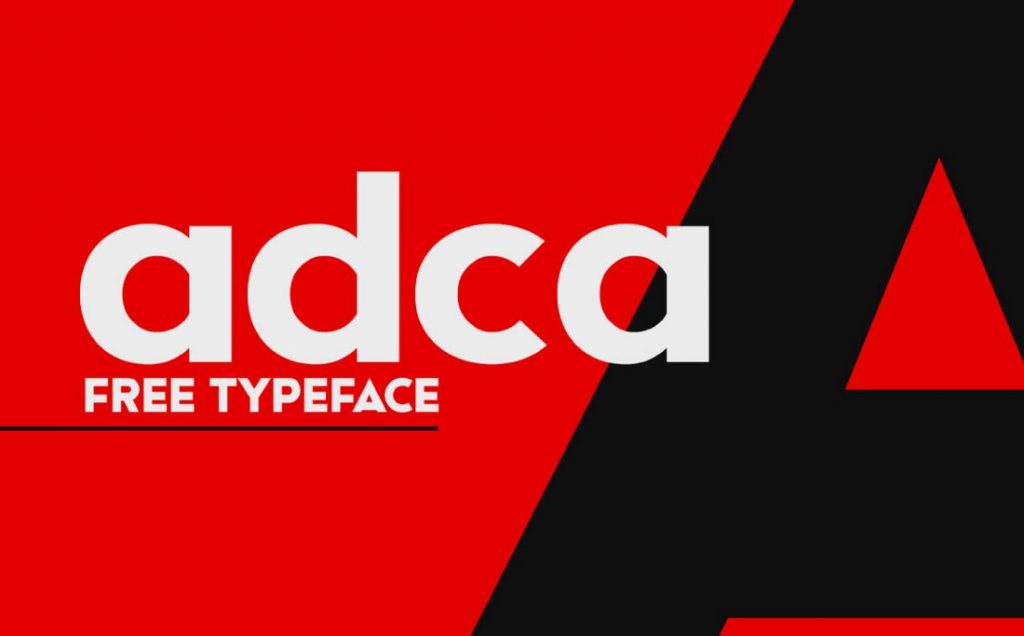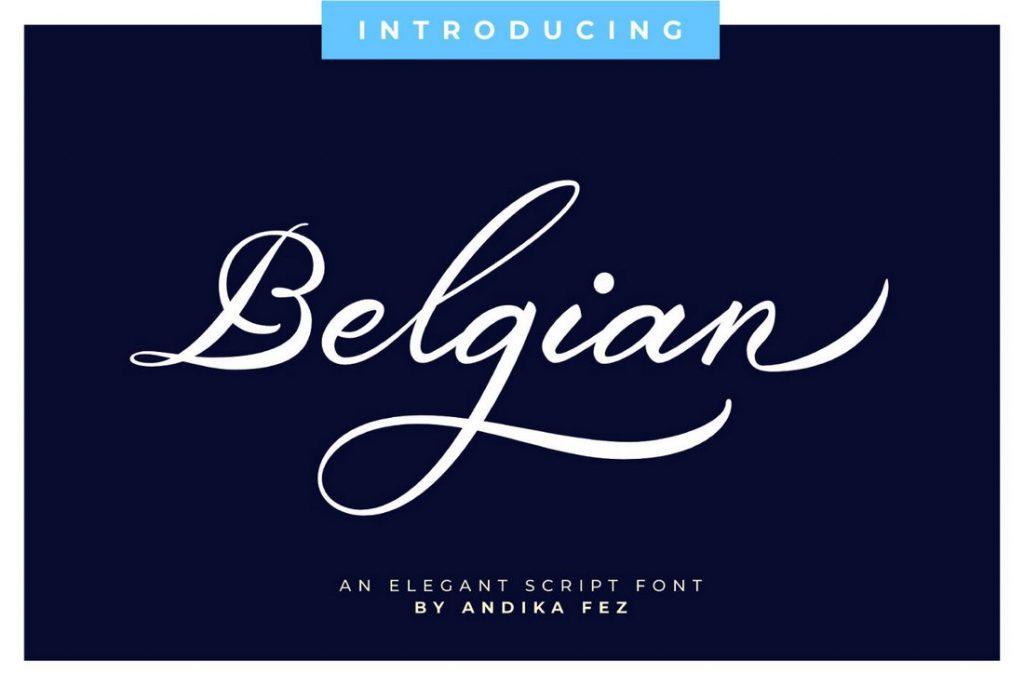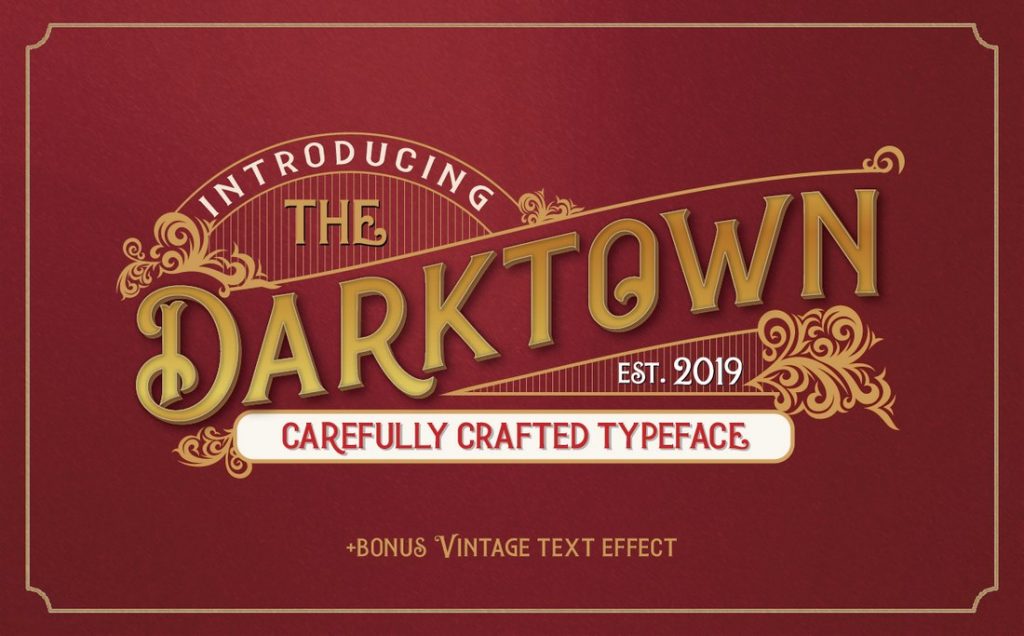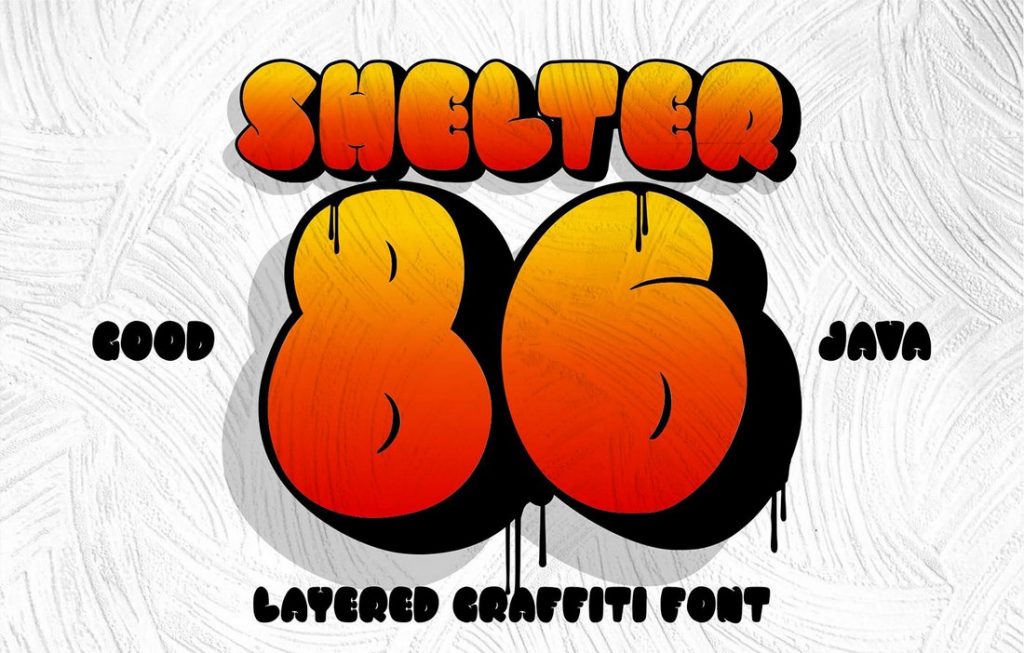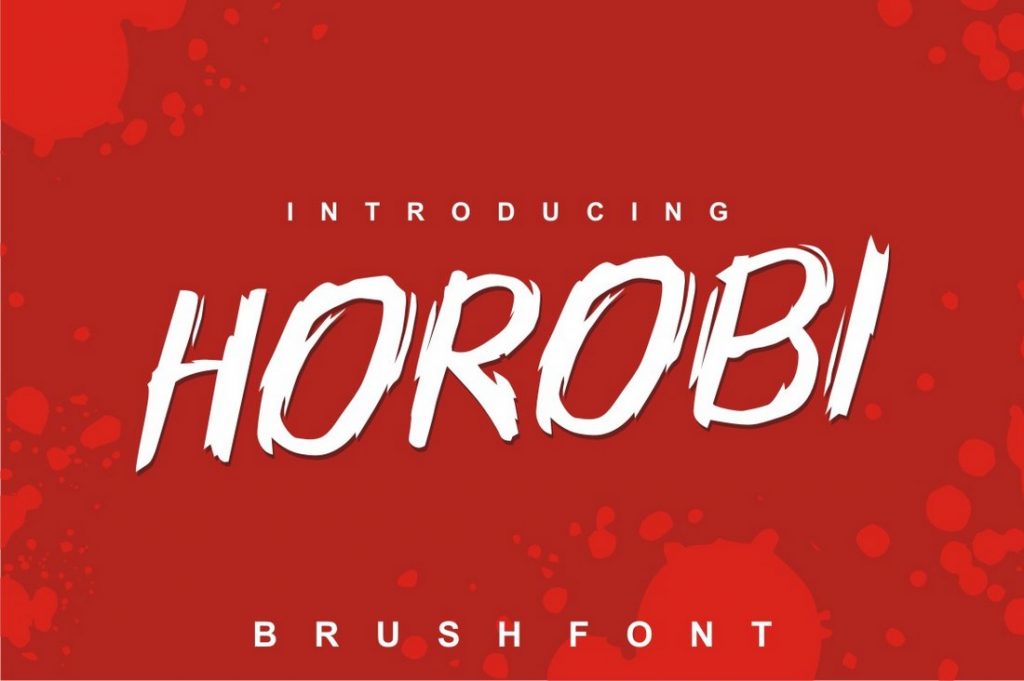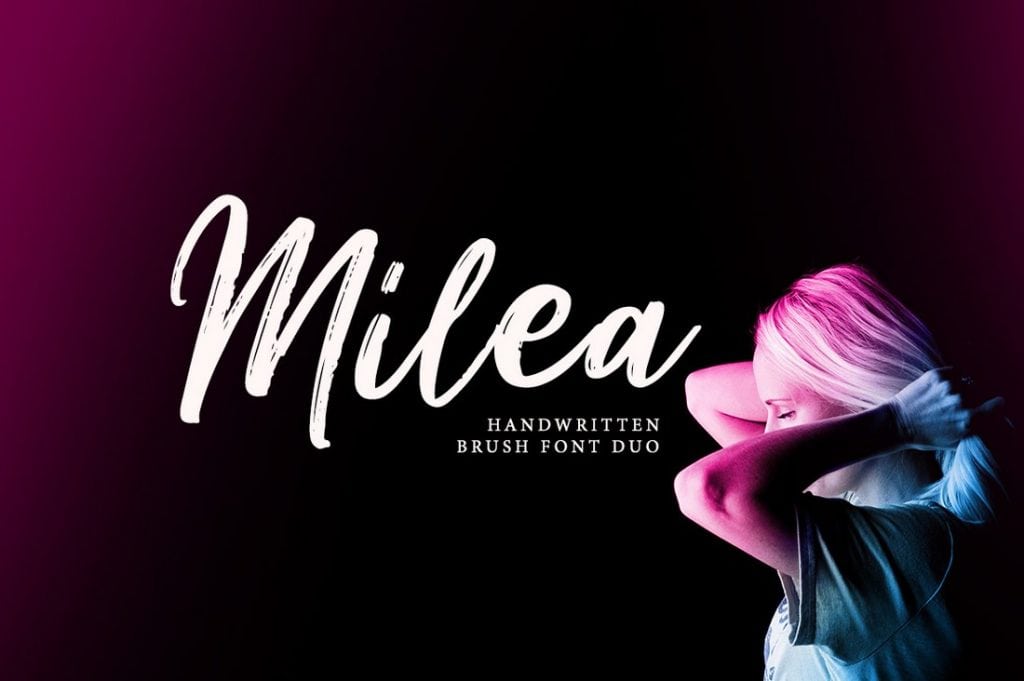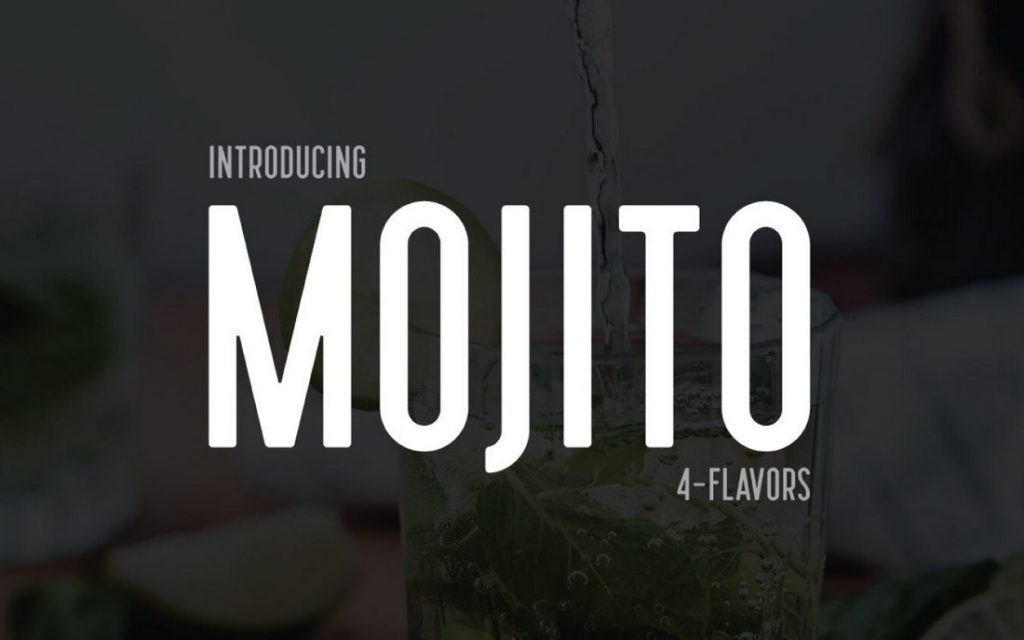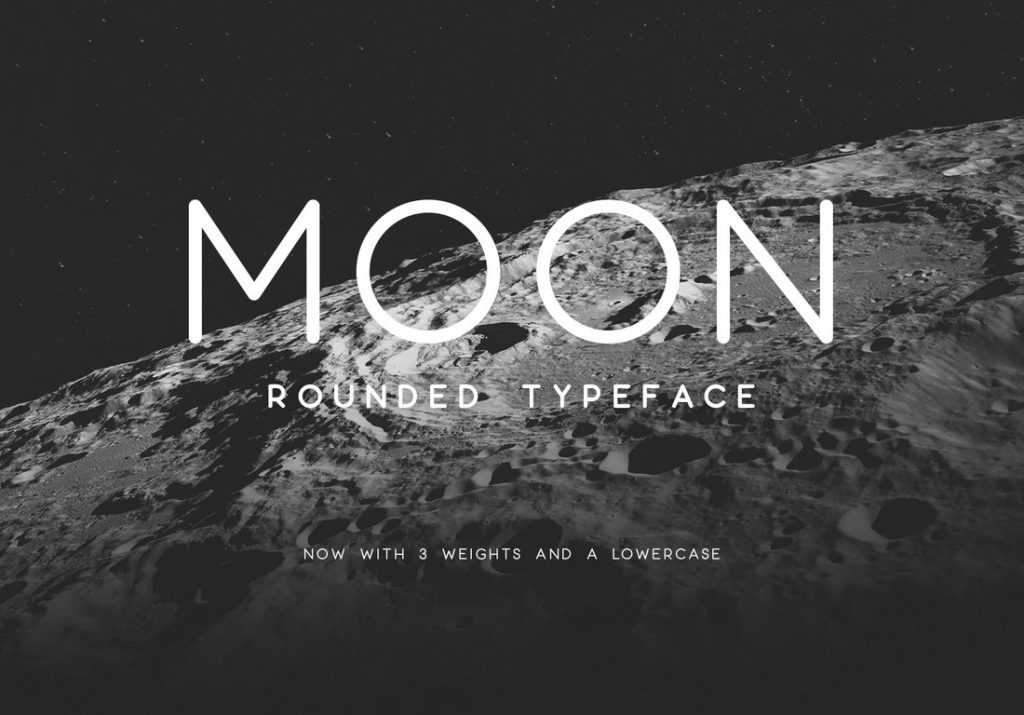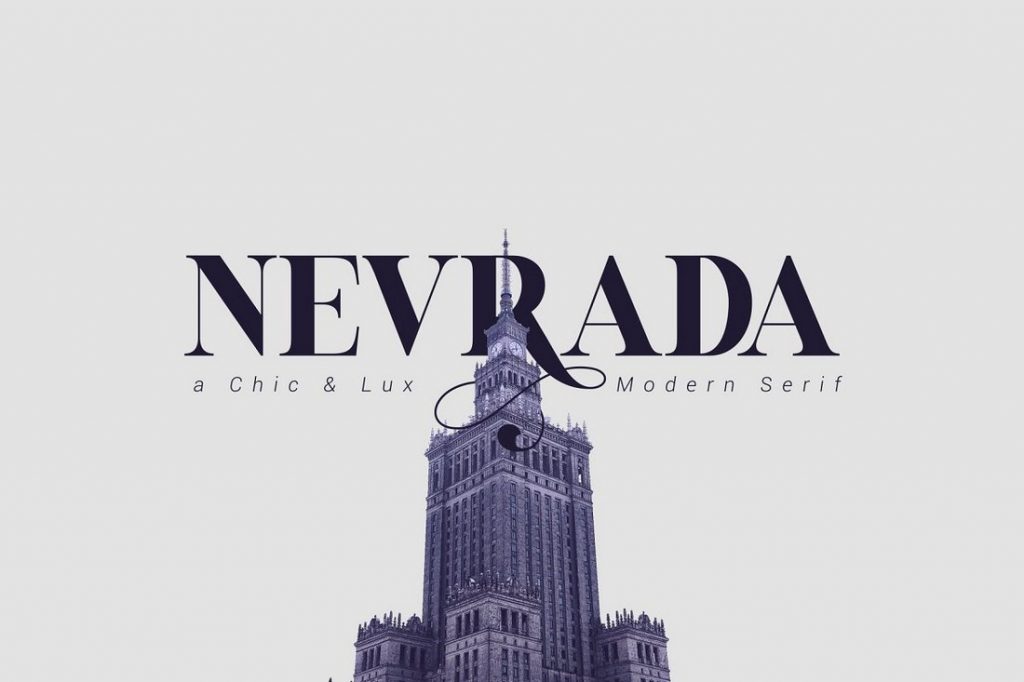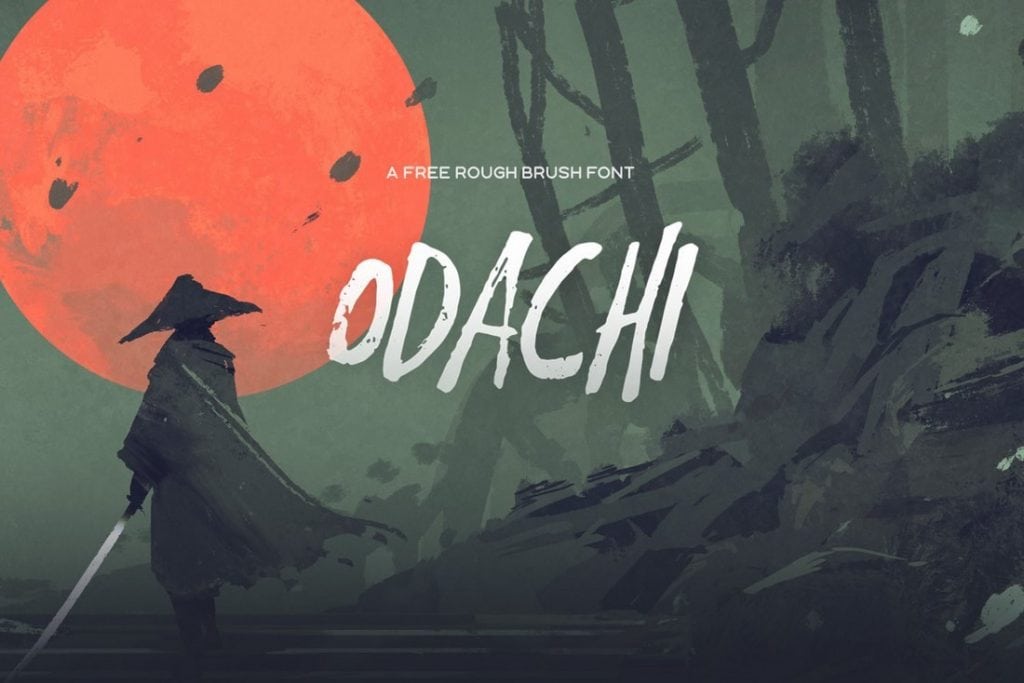
今天我們收集和整理了一些免費的字體,你將對這些字體的數(shù)量和質(zhì)量感到驚訝。 尤其是對網(wǎng)站設(shè)計或平面設(shè)計師來說,無論你是要正在尋找合適的襯線,腳本還是無襯線字體,今天希望你可以找到適合你的優(yōu)秀的免費字體!
使用美觀的字體是使任何類型的設(shè)計看起來更加專業(yè)的關(guān)鍵部分。 當然,你不必總是使用高級字體來達到相同的專業(yè)水平。 如果你無力花錢購買高級字體來使設(shè)計更加美觀,可以隨時使用數(shù)千種免費字體中的一種。
此集合中包括免費的腳本字體,襯線字體,無襯線字體,裝飾字體,以及更多與你正在從事的任何設(shè)計項目相匹配的字體。 繼續(xù),向下滾動并開始搜索下載吧。
1.Potra – Free Futuristic Font
Potra是一款具有未來派設(shè)計的現(xiàn)代字體。 該字體非常適合用于制作社交媒體帖子,T恤,網(wǎng)站設(shè)計中的標題等。
2.Milea Handwritten Brush Font
Milea是一款優(yōu)雅的筆刷字體,具有自然的手寫風格。 從書籍封面到結(jié)婚請柬,網(wǎng)站設(shè)計,博客等等,你都可以使用它來幫助你添加更多的視覺亮點。
3.Moon – Modern Rounded Typeface
Moon是一款帶有圓角字符設(shè)計的精美極簡風格無襯線字體。 該字體非常適合用于設(shè)計從網(wǎng)站設(shè)計到海報標題等等的所有內(nèi)容。
4.Nanotech – Free Clean Sans-Serif Font
Nanotech是現(xiàn)代無襯線字體,具有專業(yè)的設(shè)計。 從設(shè)計網(wǎng)站標題到海報標題,徽標等等,它都是理想的選擇。
5.ADCA – Free Bold Geometric Font
ADCA是一種使用幾何設(shè)計理念而制作的字體。 該字體可完全免費用于你的個人和商業(yè)項目。
6.Highfield – Free Luxury Sans-Serif Font
Highfield是設(shè)計奢侈品牌徽標,徽章和標牌的理想字體。 該字體可免費用于你的個人項目。
7.Belgian Signature – Free Elegant Script Font
這款優(yōu)雅的免費腳本字體具有精美時尚的設(shè)計,使其適合幾乎所有類型的不管是平面還是數(shù)字網(wǎng)頁設(shè)計,同時它可以免費用于個人和商業(yè)項目。
8.Mojito – Free Semi-Condensed Font
Mojito具有高且窄的字符設(shè)計,使其最適合設(shè)計海報和網(wǎng)頁設(shè)計中的標題。 你可以將其免費用于個人項目。
9.Tahu – Free Script Font
Tahu是一款具有簡約設(shè)計的現(xiàn)代腳本字體。 非常適合用于T恤設(shè)計,網(wǎng)站標題和社交媒體帖子。 該字體可免費用于個人和商業(yè)項目。
10.Odachi – Free Brush Font
Odachi是一款帶有粗糙設(shè)計的優(yōu)雅免費畫筆字體。 可以完全免費用于你的商業(yè)項目。 它也包括數(shù)字,替代和標點符號。
6種流行字體樣式
如果你是設(shè)計新手,那么對不同類型的字體及其使用方法有基本的了解就很重要。
1.襯線字體(Serif Fonts)
在某些字體中,你會在字符的邊緣看到較細的線條設(shè)計,擁有這個特征的字體一般稱為襯線字體。 襯線字體是具有精美字體設(shè)計的字體,它們主要用于專業(yè)和商業(yè)設(shè)計。
2.無襯線字體(Sans-Serif Fonts)
無襯線字體是具有清晰字符設(shè)計的字體。 這些字體中的字符的邊緣沒有任何線(或襯線)。 Sans-serif字體通常用于創(chuàng)意和休閑類型的設(shè)計中,而且眾所周知,它們還可以提高可讀性。
3.腳本&手寫字體(Script & Handwriting Fonts)
這些是具有漩渦狀線條和彎曲字符的字體,腳本和手寫字體在名片和文具設(shè)計中很流行。
4.復古字體(Vintage & Retro Fonts)
復古字體具有老式的字符設(shè)計,可帶你一路追溯到1900年代初,甚至回到維多利亞時代。 這些字體非常適合制作產(chǎn)品標簽和標牌。
5.涂鴉字體(Graffiti Fonts)
顧名思義,涂鴉字體是具有涂鴉風格設(shè)計的字體。 它們通常用于印刷設(shè)計中,例如T恤和海報。
6.筆刷字體(Brush Fonts)
筆刷字體具有看起來像使用畫筆繪制的字符。 這些字體是設(shè)計海報標題,書的封面等的理想選擇。
總結(jié)
這就是我們今天分享的一系列美麗而具有創(chuàng)意性的字體和字體集合。 這些字體涵蓋了幾乎所有風格的設(shè)計! 使用這些集合之一為你的下一個設(shè)計項目找到理想的字體。